악필도 괜찮아! 캘리그라피 입문 전 필수 가이드 캘리그라피(Calligraphy)는 '아름다운 글씨'라는 뜻을 가지고 있어요. 하지만 꼭 멋진 글씨체를 가진 사람만 할 수 있는 건 아니에요. 오히려 악필에서 시작해 자신만의 스타일을 찾는 경우가 훨씬 많답니다. 그래서 요즘 캘리그라피를 배우는 사람들이 점점 늘어나고 있어요.
글씨를 잘 쓰지 못해도, 캘리그라피는 누구나 도전할 수 있는 예술이에요. 중요한 건 '정확한 획'이나 '예쁜 글씨체'보다도 감성과 개성, 그리고 표현하는 마음이랍니다. 이제부터 캘리그라피를 시작하려는 분들을 위해 꼭 알아야 할 핵심들을 하나하나 알려줄게요!
📜 캘리그라피의 유래와 역사
캘리그라피의 유래와 역사
캘리그라피는 단순한 글씨체가 아니라, 오래된 예술이자 문화의 일부예요. 그 뿌리는 고대 메소포타미아 문명까지 거슬러 올라갈 수 있고, 이후 이집트와 중국, 이슬람 세계, 유럽 등에서 각기 다른 방식으로 발전했답니다. 고대 그리스어로 ‘calli’는 아름다움, ‘graphy’는 쓰기를 의미해요. 즉, '아름답게 쓰는 기술'이죠.유럽에서는 로마 시대부터 수도사들이 성경을 필사하면서 캘리그라피가 정교하게 발전했어요. 중세에는 고딕체, 르네상스 시기에는 이탤릭체 등이 등장하면서 글씨도 하나의 미술작품처럼 여겨졌죠. 반면, 중국과 일본에서는 붓글씨 문화가 캘리그라피로 계승되며 정신 수양의 도구로 여겨졌어요.
이슬람 세계의 캘리그라피는 특히 경전인 꾸란을 장식하는 데 쓰였고, 이를 통해 장식예술의 정점에 이르렀어요. 아랍문자를 곡선과 직선으로 리듬 있게 배열하는 방식은 지금도 전 세계적으로 감탄을 자아내고 있답니다.
이처럼 전 세계 각지에서 캘리그라피는 단순히 글을 적는 행위를 넘어서, 시대와 문화, 종교, 예술이 어우러진 특별한 표현 방식으로 자리 잡았어요. 현대의 캘리그라피는 디지털 기술과 만나 다양한 형태로 진화하고 있답니다. 인스타그램이나 블로그에서 감성을 전하는 글씨로 다시 각광받고 있어요!
📚 캘리그라피 시대별 특징 비교
시대 지역 특징 대표체 중세 유럽 성경 필사, 고딕체 중심 고딕체 조선시대 한국 붓글씨, 정신적 수행 강조 예서체 근현대 세계 개성 중심, 디지털 캘리 모던체 캘리그라피는 시대마다 다양한 형태로 진화했지만, 공통적으로 ‘표현’이라는 가치를 담고 있어요. 그리고 이 표현은 누구든지, 심지어 악필이어도 자유롭게 시작할 수 있는 문이에요. 이제 다음 섹션에서 왜 악필도 괜찮은지 알아볼게요! 😉
🖋 악필도 괜찮은 이유
악필도 괜찮은 이유 많은 사람들이 "나는 글씨 못 쓰니까 캘리그라피는 안 돼"라고 생각하지만, 그건 정말 큰 오해예요. 캘리그라피는 예쁘게 잘 쓰는 것보다 '자기만의 스타일을 만들어가는 과정'이 훨씬 중요하거든요. 실제로 캘리그라피 작가 중에도 원래 악필이었다는 사람들이 많답니다.
캘리그라피에서는 획이 조금 삐뚤어져도, 균형이 달라도 그 자체가 개성이에요. 오히려 너무 완벽하게 맞춘 글씨보다 약간 불완전한 느낌이 감성을 더 자극하기도 해요. 즉, 악필도 캘리그라피의 매력 포인트가 될 수 있다는 말이죠.
내가 생각했을 때, 캘리그라피는 ‘마음의 글씨’를 표현하는 도구 같아요. 단어 하나하나에 감정을 담고, 획 하나하나에 의미를 불어넣는 일이기 때문에, 잘 쓰는 것보다 얼마나 진심을 담았느냐가 더 중요해요. 그래서 누구든지 악필이어도 충분히 멋진 캘리그라피를 만들 수 있어요.
또한 캘리그라피는 연습할수록 느는 기술이에요. 처음에는 맘에 안 드는 글씨가 나올 수 있지만, 반복해서 써보다 보면 자신도 모르게 실력이 늘고 스타일도 생겨요. 결국 악필이 문제가 아니라, 시작하지 않는 게 가장 큰 장애물이랍니다!
🖌 입문자를 위한 캘리그라피 도구
입문자를 위한 캘리그라피 도구
처음 캘리그라피를 시작할 때는 고급 도구보다는 기본적인 것들로 충분해요. 오히려 너무 많은 도구를 한꺼번에 사면 부담만 커질 수 있답니다. 간단한 펜 하나와 종이만 있어도 멋진 작품을 만들 수 있어요!입문자에게 가장 추천되는 건 '브러시펜'이에요. 부드러운 붓처럼 생긴 펜으로, 두께를 자유롭게 조절할 수 있어 다양한 스타일을 연습하기 좋아요. 대표적인 제품으로는 Tombow, 모나미 붓펜, 펜텔 펜 등이 있어요.
종이는 일반 A4용지보다는 약간 도톰한 재질의 캘리 전용지를 쓰는 게 좋아요. 너무 얇은 종이는 잉크가 번지거나 찢어질 수 있거든요. 마트나 온라인 문구점에서도 쉽게 구할 수 있으니 부담 없이 시작할 수 있어요.
연습용으로는 연습노트도 좋아요. 기본 획, 글자 구조, 좌우 밸런스를 익히기에 딱이에요. 요즘엔 유튜브에서 무료로 따라 쓰기 영상도 많아서, 도구 몇 가지만 있으면 집에서도 충분히 연습할 수 있어요. 🏡
🖍 캘리그라피 입문 도구 비교표
도구 종류 특징 입문 추천 펜 브러시펜 획 조절이 쉬움 ★ ★ ★ ★ ★ 종이 캘리전용지 번짐 방지 ★ ★ ★ ★ 노트 연습노트 기본 구조 연습용 ★ ★ ★ ★ 도구는 점점 다양해지지만, 중요한 건 '내 손에 익는 것'을 찾는 거예요. 부담 없이 시작해보는 것, 그것만으로도 이미 반은 성공이랍니다! 🥰
🎨 기초 캘리그라피 스타일 4가지
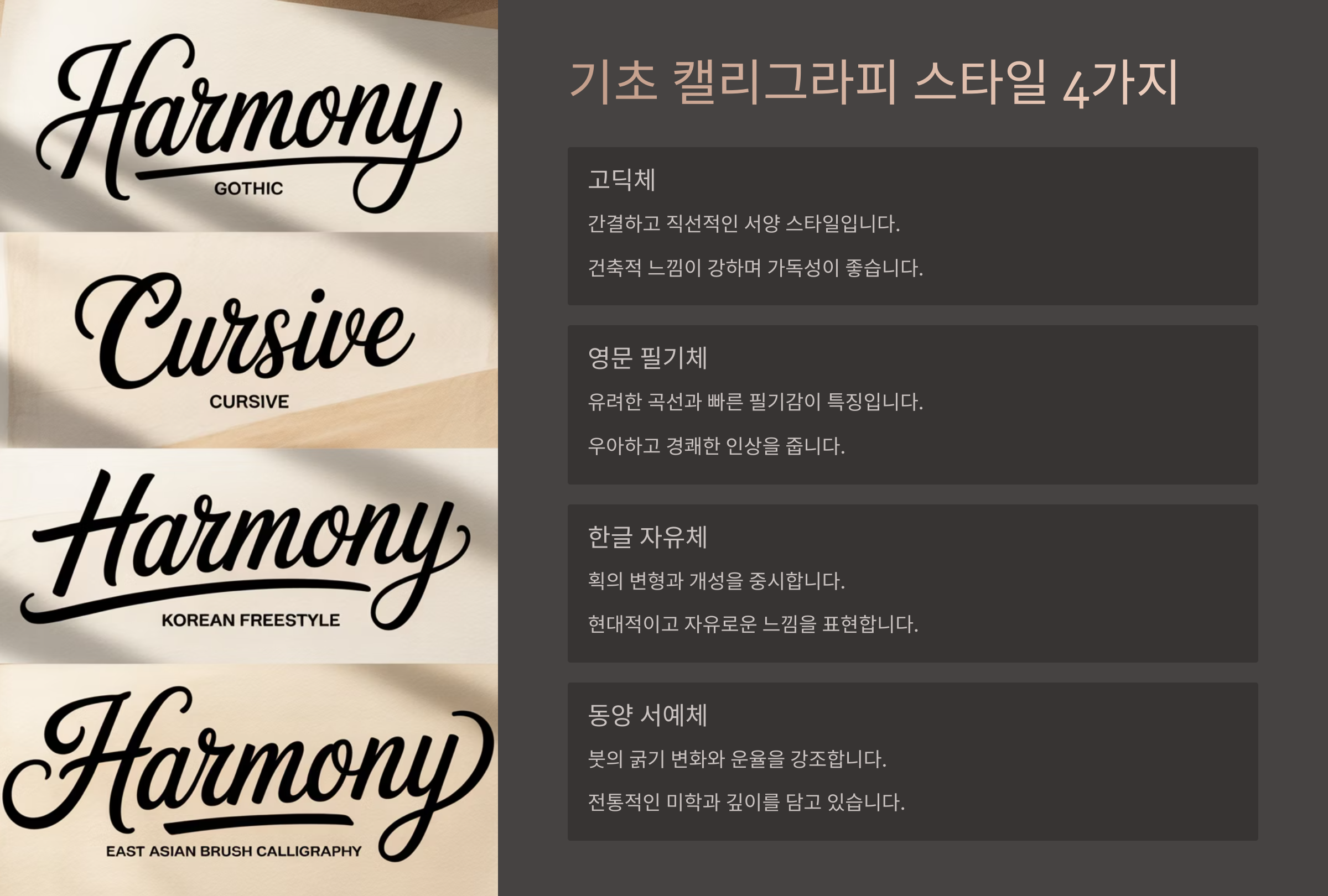
기초 캘리그라피 스타일 4가지
캘리그라피는 스타일이 정말 다양해요. 같은 단어라도 어떤 스타일로 쓰느냐에 따라 완전히 다른 분위기가 연출되죠. 입문자라면 가장 기본이 되는 네 가지 스타일을 먼저 익히는 걸 추천해요. 각각의 특징을 알아두면 연습 방향이 뚜렷해지거든요.첫 번째는 '브러시 스타일'이에요. 브러시펜을 사용해 굵기 조절을 하며 부드러운 곡선과 강약 있는 획을 표현하는 방식이에요. 감성적인 느낌이 강해 일기장이나 포스터에 자주 쓰여요.
두 번째는 '모노라인 스타일'이에요. 획 굵기가 거의 일정해서 깔끔하고 현대적인 분위기를 줘요. 마치 타이포그래피 느낌도 나기 때문에 로고 디자인에도 자주 활용돼요.
세 번째는 '고딕 스타일'인데요, 중세 유럽의 글씨체를 기반으로 한 스타일이에요. 획이 각지고 선명해서 포스터나 타이틀에 쓰면 존재감이 확 살아나요. 마지막 네 번째는 '펜 캘리그라피'로, 딥펜이나 붓펜을 이용한 전통적인 방식이에요.
📝 캘리그라피 스타일별 특징 정리
스타일 도구 느낌 추천 용도 브러시 스타일 브러시펜 부드럽고 감성적 포스터, 노트 모노라인 펜 깔끔하고 단정함 로고, 웹디자인 고딕 스타일 딥펜 강렬하고 중세 느낌 타이틀, 간판 펜 캘리그라피 붓펜, 딥펜 전통적이고 고풍스러움 작품, 엽서 처음에는 스타일 하나를 정해서 집중 연습해보는 게 좋아요. 점점 익숙해지면 스타일을 섞어 쓰거나 자신만의 방식으로 변형해보는 것도 캘리의 묘미랍니다. 😊
✏ 연습 방법과 꿀팁
연습 방법과 꿀팁 캘리그라피는 매일 조금씩이라도 손에 익히는 게 중요해요. 그래서 하루에 10분만 투자해도 실력이 쑥쑥 늘 수 있답니다. 연습은 무작정 쓰기보다는 기본 획부터 차근차근 따라가는 게 좋아요.
처음엔 가이드라인이 있는 연습장을 활용하면 좋아요. 기본적으로 점, 선, 곡선을 반복 연습하면서 펜의 압력과 방향에 익숙해질 수 있어요. 이런 연습은 글씨의 균형감도 키워준답니다.
영어 알파벳이나 한글 자음을 반복해서 써보는 것도 도움이 돼요. '가나다' 또는 'ABC'를 쓰며 모양을 분석하고, 획 순서를 익히는 과정이 중요해요. 글씨가 맘에 들지 않아도 자책하지 말고 꾸준히 써보세요!
자신이 좋아하는 문장을 따라 쓰는 것도 추천해요. 명언이나 좋아하는 가사 한 줄을 캘리그라피로 표현하면 감성도 담고 연습도 되는 일석이조! 가끔은 다른 사람의 작품을 보고 모방하는 것도 실력을 높이는 좋은 방법이에요.
📦 캘리그라피의 활용 예시
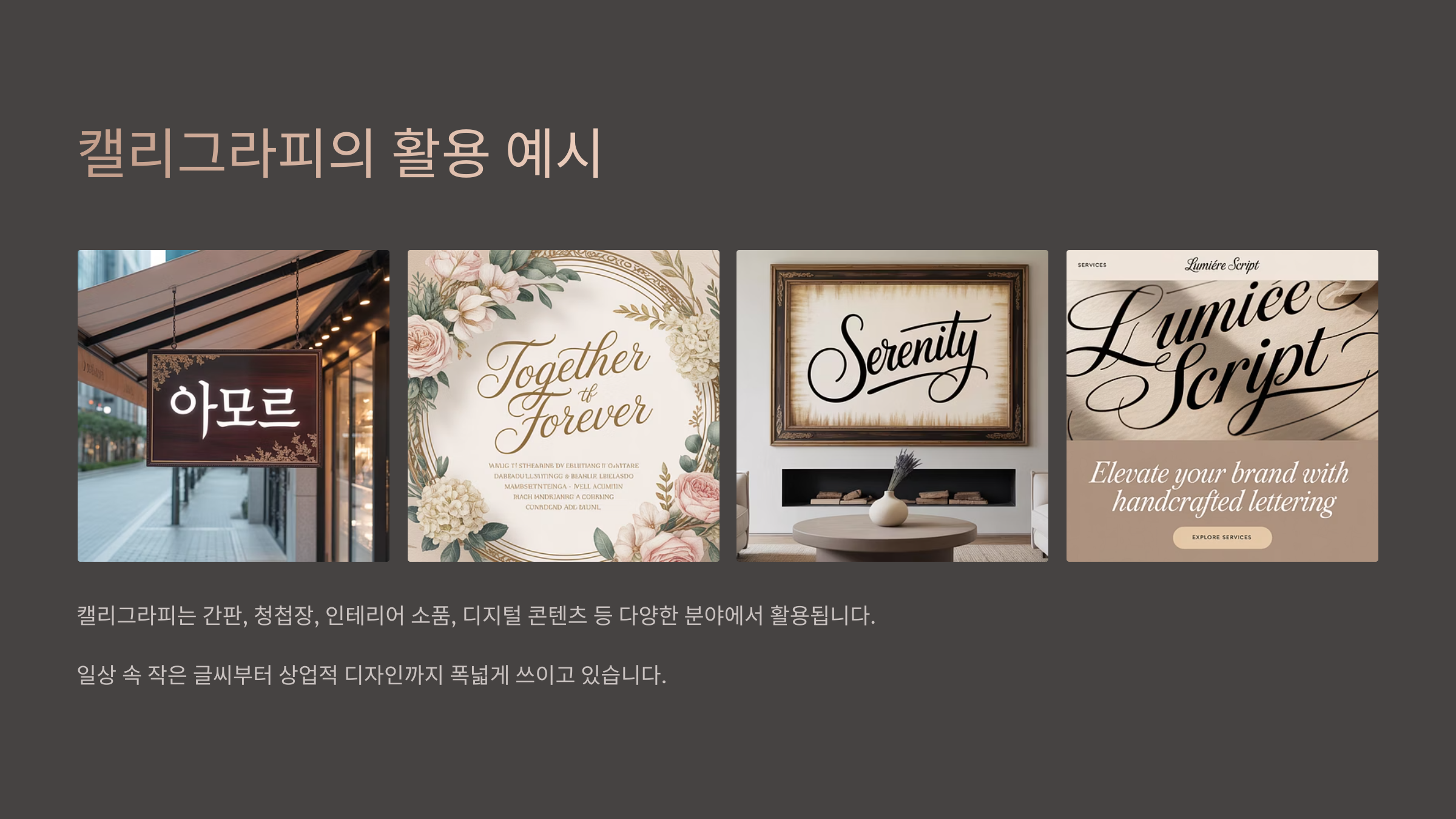
캘리그라피의 활용 예시
캘리그라피는 단순한 취미를 넘어서 일상 속에서 다양하게 활용할 수 있어요. 예를 들어, 다이어리나 플래너에 직접 쓴 제목만으로도 하루가 더 감성적으로 시작될 수 있답니다.손편지나 카드에 직접 쓴 글씨를 넣으면 받는 사람도 감동을 느껴요. 요즘은 웨딩 캘리그라피처럼 결혼식 청첩장이나 데코용으로도 많이 활용되고 있어요. 감성적인 분위기를 더하는 데 딱이에요.
또한 소셜미디어 콘텐츠에도 캘리그라피가 자주 쓰여요. 인스타그램 피드에 직접 쓴 글귀를 올리면 개성과 감성이 물씬 풍기거든요. 필터나 배경 없이도 글씨 하나로 감동을 줄 수 있어요.
심지어 캘리그라피는 상품 패키지 디자인, 간판, 광고, 명함 등에서도 활용되고 있어요. 디지털 시대에도 아날로그 감성의 글씨가 사람들의 마음을 사로잡는 이유는 분명하죠. ✨
Q1. 캘리그라피는 악필이어도 잘할 수 있나요?A1. 물론이에요! 잘 쓰는 것보다 감성과 표현이 더 중요하답니다.
Q2. 어떤 펜을 사야 하나요?
A2. 입문자에겐 브러시펜이 가장 좋아요. Tombow나 펜텔을 추천해요.
Q3. 종이는 아무거나 써도 되나요?
A3. 번짐 없는 도톰한 캘리 전용지를 사용하는 게 좋아요.
Q4. 얼마나 연습해야 실력이 느나요?
A4. 하루 10분씩만 꾸준히 해도 한 달 안에 눈에 띄는 변화가 생겨요!
Q5. 독학해도 괜찮을까요?
A5. 요즘은 유튜브나 무료 강의가 많아서 독학으로도 충분해요.
Q6. 작품은 어디에 올리면 좋을까요?
A6. 인스타그램, 블로그, 핀터레스트에 많이 올려요. 해시태그 활용도 좋아요!
Q7. 디지털 캘리그라피도 배우고 싶어요!
A7. 아이패드와 Procreate 앱으로 연습할 수 있어요. 브러시도 다양하게 있어요.
Q8. 내 스타일을 찾으려면 어떻게 해야 하나요?
A8. 여러 스타일을 시도해보고, 그중에 가장 편하고 마음에 드는 걸 계속 써보세요!